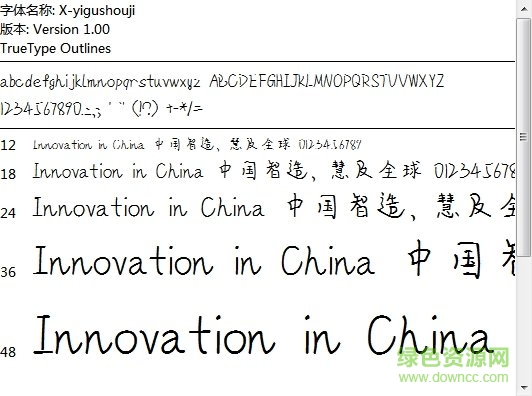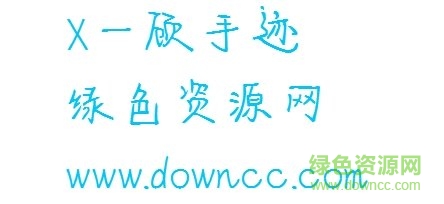
一顧手跡是x手跡字體推出的一款手寫體,筆畫清晰柔和,無過多的修飾和特意的轉(zhuǎn)合之勢,給文字最原始最樸素的風(fēng)格體驗(yàn),讓你有著極佳的視覺呈現(xiàn),喜歡就來綠色資源網(wǎng)試試吧!
一顧手跡體由X手跡工作室打造,清新質(zhì)樸、秀氣和諧,不會過于潦草、不會過于尖銳,有著十分舒適的藝術(shù)美感,用于手機(jī)字體閱讀、平面設(shè)計、印刷打印等場合均可。